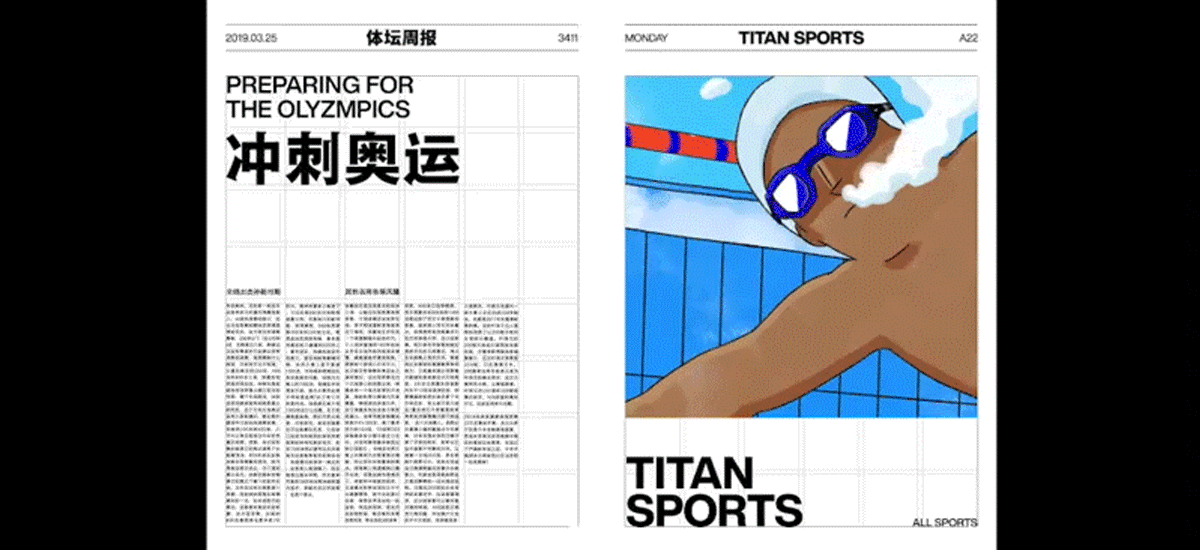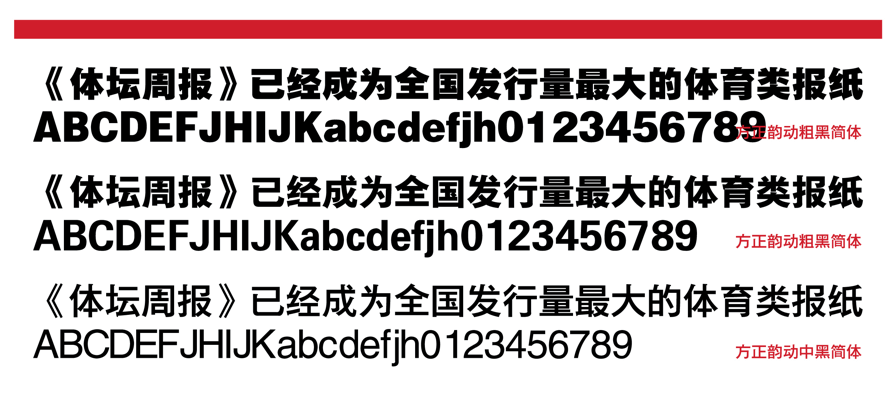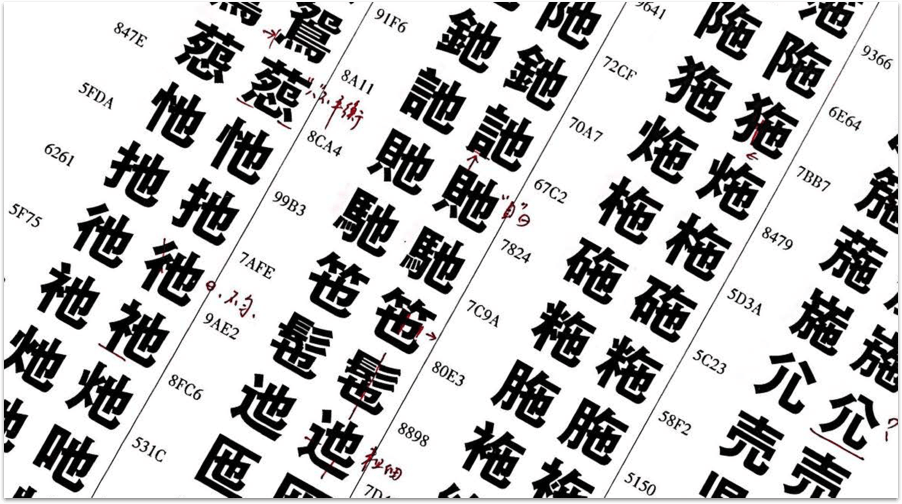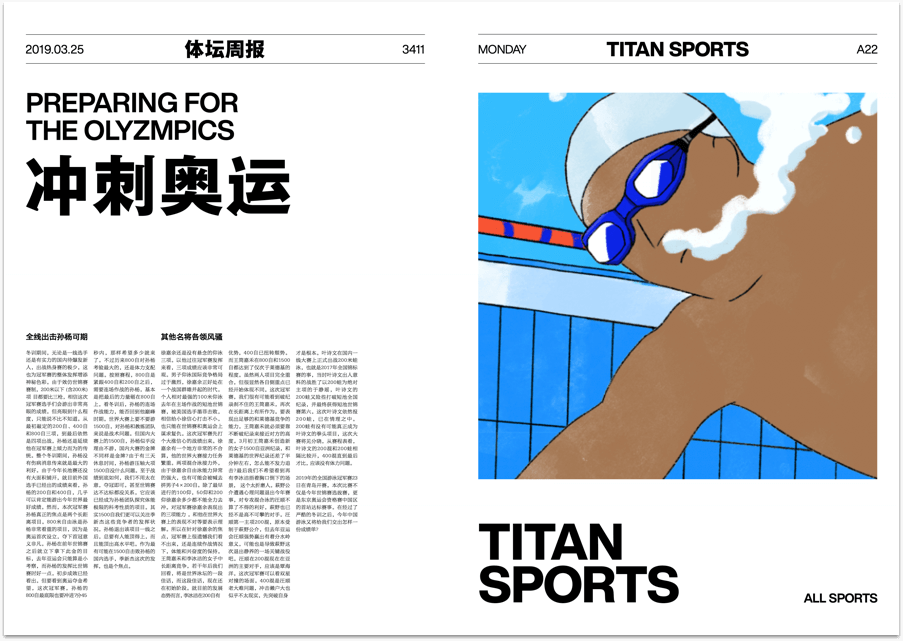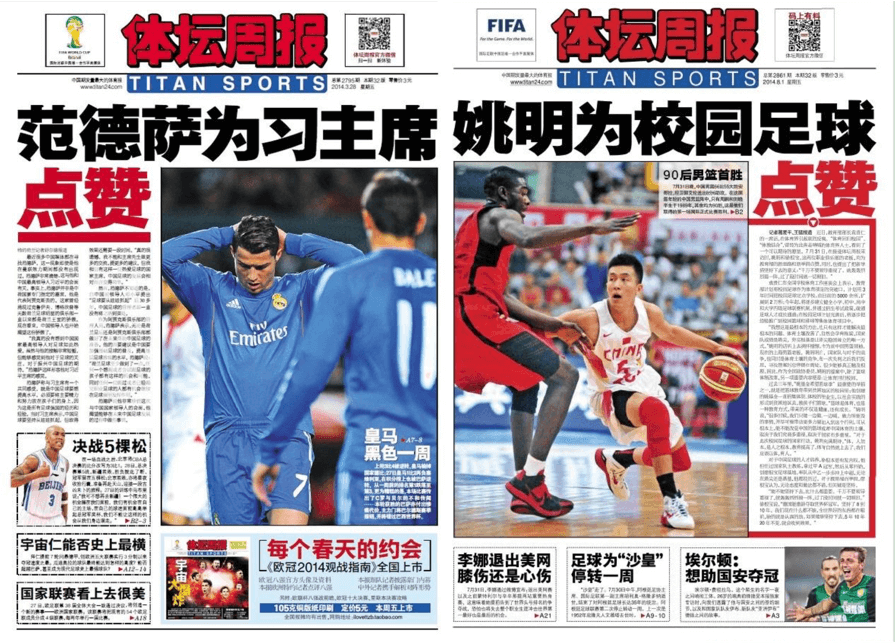
方正韵动黑系列字体
2004
韵动黑是一款粗细形成系列化的,时尚、个性的家族字体,这款字体专门针对报社的实际需求而设计,在单字的设计上更趋个性化。
这种系列字体的推广有利于报社进行主、副标题的配合,更能满足报社的实用需求。
韵动黑根据粗细不同分为方正韵动特黑、方正韵动粗黑和方正韵动中黑三款。
韵动黑系列字体在竖、撇、提的起笔处增加了装饰头,使字体更具个性。在撇、捺、点的设计上力求角度自然合理,并对字面适当加以扩大,使字体更加庄重平稳,增强了版面的视觉冲击力。韵动黑为系列字,涵盖大标题,中标题,小标题及正文,并配有非常适合比赛报道的专用符号库。
与以往黑体最大不同是去掉了原黑体笔画上的喇叭口装饰,使字体风格更加简约时尚,令人耳目一新。字体在笔形、结构上的风格完全一致,而粗细方面则分为细中粗三档,有效的解决了原字库中黑体、大黑、超粗黑的风格不一致、搭配时不协调的问题。
韵动体实际应用场景